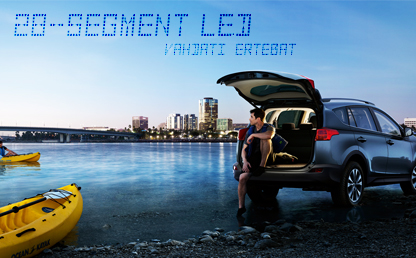
فونت زیبای LED ( نمایشگر ۲۸ سگمنتی ) 16 سپتامبر 2013رسول وحدتی 28-Segment LED | 1 TTF | 41.9 KB | By Vector Art این فونت یکی از فونتهای زیبا و فانتزی انگلیسی بوده که توسط vector art طراحی شده است . شما میتوانید در طرحهای خود از این فونت زیبا استفاده نمایید . امیدوارم این فونت مورد پسند شما قرار بگیرد . :: دانلود : http://trainbit.com/files/6123529884/28-Segment-LED.ttf 36.702008 52.659187 امتیاز بدهید:به اشتراکگذاری :بیشتر اشتراکگذاری در X (در پنجرۀ تازه باز میشود) X به اشتراک گذاشتن در فیسبوک (در پنجرۀ تازه باز میشود) فیسبوک چاپ (در پنجرۀ تازه باز میشود) چاپ ایمیلکردن یک پیوند به یک دوست (در پنجرۀ تازه باز میشود) رایانامه اشتراکگذاری در ردیت (در پنجرۀ تازه باز میشود) رددیت اشتراکگذاری در لینکدین (در پنجرۀ تازه باز میشود) لینکداین اشتراکگذاری در پینترست (در پنجرۀ تازه باز میشود) پینترست اشتراکگذاری روی تامبلر (در پنجرۀ تازه باز میشود) تامبلر اشتراکگذاری در واتساپ (در پنجرۀ تازه باز میشود) واتساپ اشتراکگذاری در تلگرام (در پنجرۀ تازه باز میشود) تلگرام لایک در حال بارگذاری... مرتبط